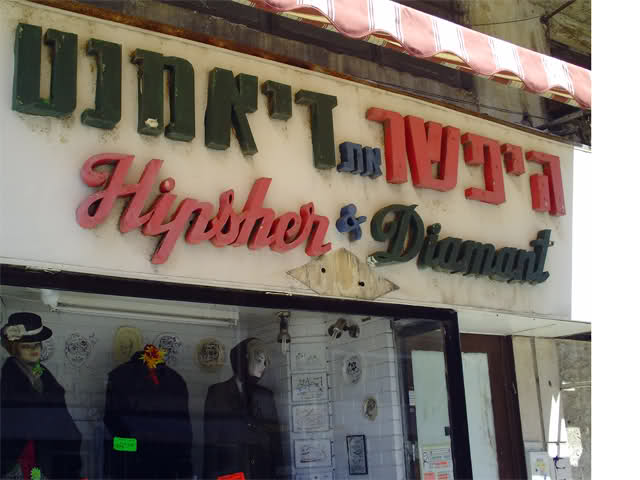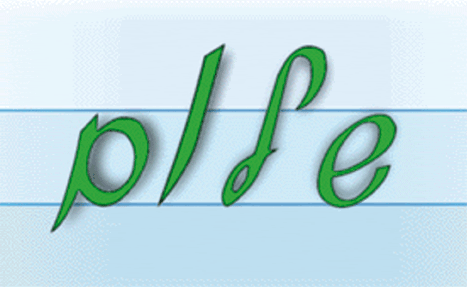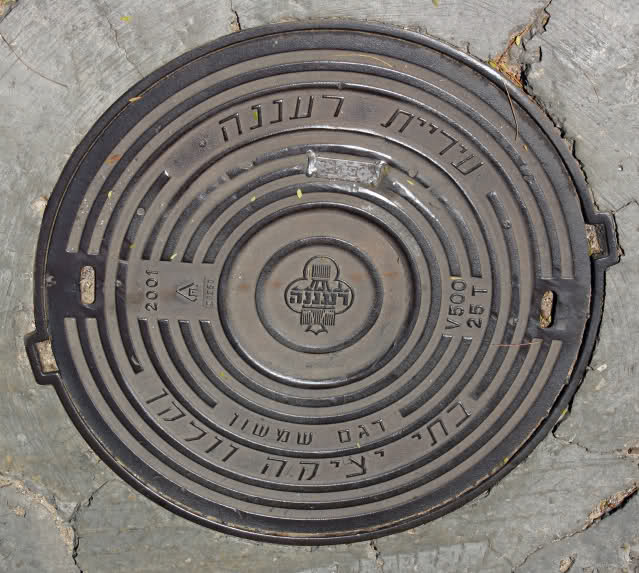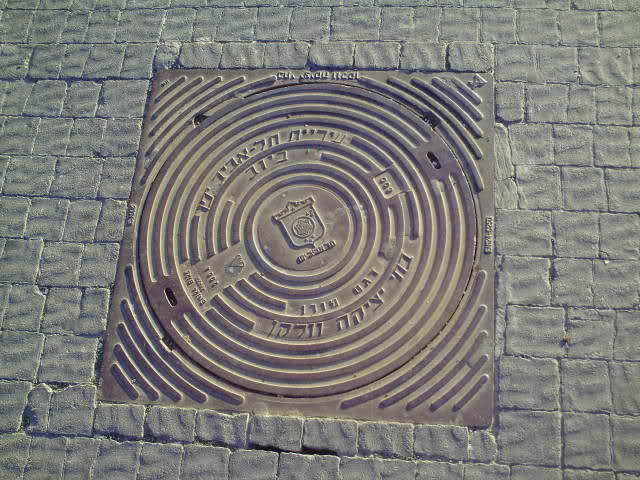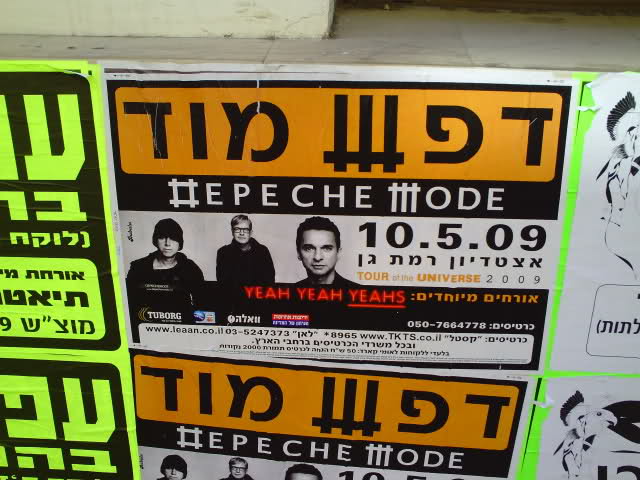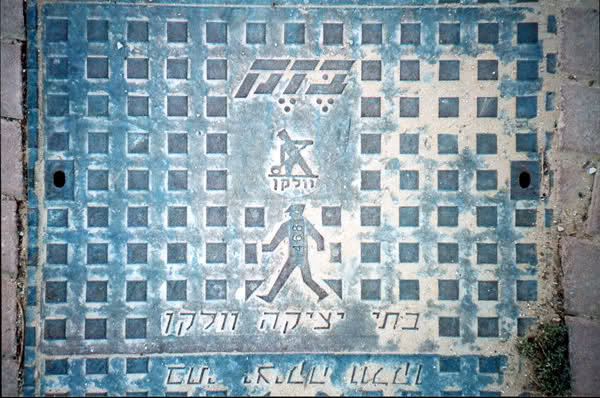
„Hebräische Kursivschrift“
Warum ist die „Hebräische Kursivschrift“ (Handschrift) leicht nach rechts geneigt?
Auch die Druck-Italics die ich aus dem Hebräischen so kenne,
neigen sich alle nach rechts.
Es wird von rechts nach links geschrieben und gelesen.
Warum? Das ist doch gegen den Schreib- und Lesefluss?
Die hebräische Kursiv als Handschrift ist eigentlich ziemlich geradstehend.
Die kursiven Druckschriften sind wahrscheinlich ein Sonderfall; bei strenger historischer Betrachtung dürfte es die wohl genausowenig geben wie kursive Frakturschriften, weil das dem Duktus und der Entstehung der Schrift widerspricht. Vermutlich sind diese kursiven Druckschriften also reine Kunstprodukte. Da diese wahrscheinlich frühestens ab der zweiten Hälfte des zwanzigsten Jahrhunderts entstanden sind, werden sich die Gestalter in der Kursivlage einfach an die lateinischen Kursiven angelehnt haben, mit denen die meisten ja auch großgeworden sind. Denn die lateinischen Schriften sind ja allen in Frage kommenden Gestaltern sehr präsent, seien das nun europäische oder amerikanische Juden oder Einwanderern nach Israel. Die Wiederbelebung der hebräischen Schrift als Alltagsschrift ist ja historisch unwahrscheinlich jung. Und selbst die Sabres, also die in Israel geborenen, die ja die einzigen sind, die die hebräische Schrift als erste Schrift in der Schule gelernt haben, sind mit den lateinischen Alphabeten bestens vertraut.
mh ...
Wenn man sich Schriftproben der Handschrift ansieht,
ist es doch deutlich zu erkennen, dass diese sich nach rechts neigt!
Vor allem wenn man ein Lehrbild ansieht?
Kann es sein dass, auch wenn von rechts nach links geschrieben wird, die rechte Hand den Stift trotzdem von rechts unten hält und nicht von rechts oben, und die Neigung der Schrift einen rechten Winkel auf diese Haltung bildet? :?
Genau das wollte ich auch grad schreiben. Auch wenn man von rechts nach links schreibt und liest, sind die meisten halt Rechtshänder, und damit ergibt sich aus der Handgelenksbewegung ein sehr leichtes SW-NO, aber nur umständlich ein NW-SO (Himmelsrichtungsartig gedacht).
Ich bin gerade in Israel und kann bestätigen, daß die "Handschrift" deutlich nach rechts geneigt ist, jedenfalls auf allen Plakaten und Werbepostern im Straßenbild. Ich werde morgen mal unsere hiesigen Freunde danach fragen.
Aktuell habe ich schon genug damit zu tun, anhand von Straßenschildern und hartnäckigem Nachfragen die Grundzüge der Schrift zu lernen; es gibt viele Ausnahmen und vieles müsse man "einfach wissen". Tja.
Also meine israelischen Freunde meinen, dass die Neigung der meisten Handschriften daher komme, dass eben Rechtshänder nach links schreiben müssen und dann komme das dabei heraus.
Ich werde morgen mal ein paar typographische Impressionen sammeln, gerne auch Kanaldeckel. Insgesamt scheint die typographische Vielfalt im Hebräischen geringer zu sein als in der lateinischen Schrift. Immer noch kompliziert genug. Erst allmählich lösen sich einzelne Buchstaben in meiner Wahrnehmung aus dem Zeichenbrei, ich erkenne häufige Kombinationen wieder; aber wenn ich es dann vorlesen lasse, klingt es doch anders, weil im Alltag die Vokale nur teilweise und dann auch noch mehrdeutig notiert werden. Und: "B" kann auch "W" sein, "P" kann auch "F" sein, für "K" gibt es zwei Zeichen, das eine kann aber auch "CH" bedeuten. Klingt verwirrend? Ist es auch. Aber lustig, wenn man es nur zum Spass mal "an"lernt. Wenn man es richtig lernen wollte oder müsste, wäre es schon ein Stück Arbeit. Respekt vor den Theologiestudenten.
Wenn man es richtig lernen wollte oder müsste, wäre es schon ein Stück Arbeit. Respekt vor den Theologiestudenten.
Hebräisch lernen ist ganz einfach. Schon nach wenigen Jahren ist der Einwanderer in der Lage, einen Passanten in fließendem Hebräisch zu fragen: »Können Sie mir bitte sagen, wie spät es ist, aber wenn möglich, auf Englisch.« (frei nach Kishon, aus dem Kopf citiert)
Ja, bitte, auch israelische Kanaldeckel.
Einen (wenn auch nicht die tollste Fotoqualität – dafür aber auch mit geneigter Schrift!) kann ich anbieten:
Wenn ich es richtig lese (mein Hebräisch ist sehr, sehr basic :( ) steht da:
????? (bezek), mit Vokalzeichen, da es sich um einen Eigennamen handelt (vermutlich: Bezeq – The Israel Telecommunication Corp.)
??? ????? ????? = batei yetsika vulkan = Vulkan Gießereien
Wow, toll!
Was steht denn unter dem Männchen mit dem großen Suppenlöffel? :hammer:
Habe heute auftragsgemäß einen "Püttdeckel" geknipst (hatte meine gute Kamera nicht dabei, aber der kleine Videorecorder vom Aldi kann auch Fotos aufnehmen).
Morgen werde ich noch mal mit dem besseren Gerät auf Jagd gehen nach Gullydeckeln und reizvoller Typographie.
Hier ist ab morgen abend Pessach, ein hoher Feiertag, Museen geschlossen, alles kauft noch wie wild ein; sieben Tage ohne reguläres Brot und so stehen an.
das ist sicherlich ein gießer.
Ha! Das ma… ergibt Sinn, ja. Ich hatt's echt nicht geschnallt.
Heute noch einen Deckel abgelichtet:
Ach ja: Interessiert jemanden ein Bild (oder mehrere) von aparter hebräischer Typographie im Strassenbild oder Ladenschilder mit der hebräischen und der lateinischen Darstellung gleicher Namen?
frechheit. was soll die frage. wo sind wir hier? :lol:
JA, JA, JA! :biglove:
Hübscher und Diamant, Damenmode in Tel Aviv, mit farbiger Zuordnungshilfe für die Buchstabensucher...
Nicht immer sind gleichaussehende Zeichen auch gleichbedeutend:
Obere Zeile von rechts nach links: D P Sch / M O D
D P Sch / M O D
DAS ist ja krass.
Frage: Ist das "#"-artige Zeichen, das in "DEPECHE" das "D" ersetzt hat, ein hebräisches?